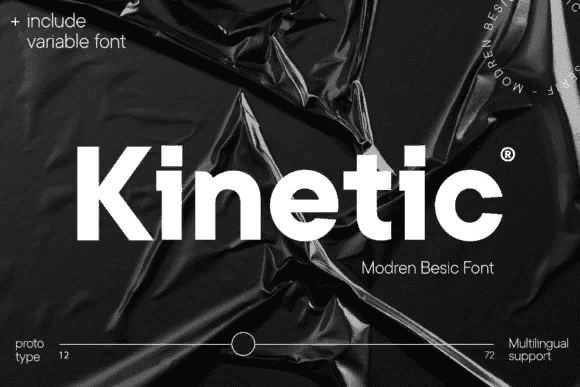
Название: Kinetic Font (2021)
Kinetic - это современный и крутой шрифт без засечек.
Его можно легко подобрать к невероятно большому набору проектов, поэтому добавьте его в свои творческие идеи и обратите внимание, как он выделяет их!
Название: Kinetic Font (2021)
Kinetic - это современный и крутой шрифт без засечек.
Его можно легко подобрать к невероятно большому набору проектов, поэтому добавьте его в свои творческие идеи и обратите внимание, как он выделяет их!